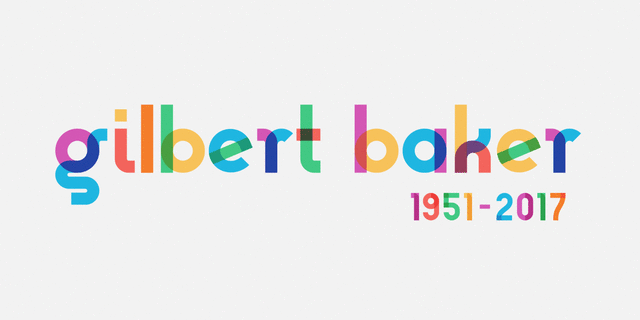
31 марта 2017 года скончался Гилберт Бейкер – создатель знаменитого Радужного Флага. Он был активистом LGBTQ, художником, и был известен тем, что помогал друзьям создавать баннеры для протестов и маршей. Чтобы почтить память Гилберта Бейкера, NewFest и NYC Pride вместе с Ogilvy & Mather и создателями шрифтовых инструментов Fontself создали бесплатный шрифт по мотивам Радужного Флага. Этот шрифт был назван «Gilbert» в честь Гилберта Бейкера.
Шрифт Gilbert предназначен для ярких заголовков и лозунгов на баннерах для митингов и протестов. Демо-версия Gilbert доступна на сайте typewithpride.com в двух вариантах, в виде стандартного векторного OpenType шрифта, который можно использовать в любом приложении и цветного шрифта OpenType-SVG, который можно использовать в Photoshop CC 2017.
Символы шрифта создавались в Illustrator CC, а затем они были преобразованы в файлы шрифтов с помощью специального плагина для создания шрифтов Fontself for Illustrator, адаптированного специально для генерации цветных векторных шрифтов.